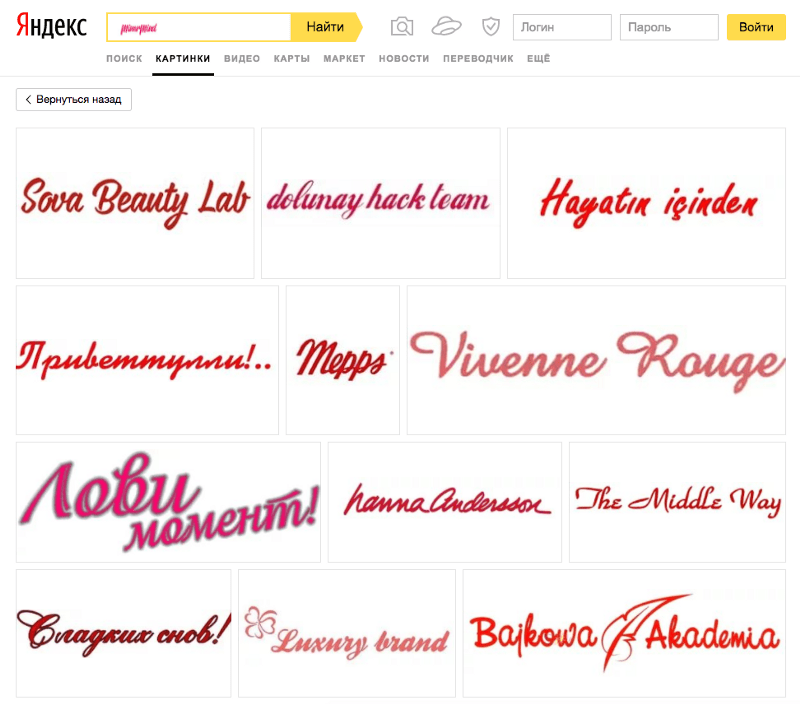
Как выбрать шрифт — руководство для начинающих — Офтоп на vc.ru
Дизайнер и разработчик Джонатан Уайт рассказал о базовых принципах работы с типографикой.
Один из самых важных навыков для дизайнера — это умение выбирать типографику, пишет Джонатан. Ведь текст — один из основных способов коммуникации дизайнера с пользователями. И типографика может как улучшить дизайн, так и сломать его.
Типографика одновременно сложна и прекрасна. Некоторые люди посвящают ей всю свою карьеру. К счастью, их работа хорошо задокументирована, так что у нас есть множество типографических онлайн-ресурсов.
Этот материал призван сформировать начальные навыки выбора типографики для своего дизайна, а также стимулировать на эксперименты со шрифтами и их комбинациями — в том числе и неизвестными.
Определите свою цель
Прежде всего нужно понять, в чем цель вашего дизайна. Какую информацию вы хотите донести? С помощью чего? В хорошем дизайне типографика соответствует цели.
Например, если вы создаете дизайн приветственной карточки, который в основном полагается на изображения, лучше выбрать шрифт, который подходит к стилю иллюстраций. Шрифт должен находиться в гармонии с остальным дизайном.
Выбирайте шрифт, соответствующий стилю иллюстраций
Если вы создаёте дизайн лендинга, в котором большую роль играют изображения, берите шрифт, который не будет отвлекать от иллюстраций. Шрифт в этом случае выступает как способ сделать акцент на значимой информации, несущей ключевой смысл.
Если изображения — главный элемент вашего дизайна, берите простые шрифты, чтобы подчеркнуть иллюстрацию
Определите свою аудиторию
Разобравшись с целью дизайна, определитесь с аудиторией. Этот шаг крайне важен, поскольку выбор шрифтов будет зависеть от возраста, интересов и культурного бэкграунда аудитории.
Например, некоторые шрифты лучше подходят для детей. Поскольку они только учатся читать, для них лучше всего подходят легкочитаемые шрифты с крупными и различимыми буквами. Хороший пример такого шрифта — Sassoon Primary. Его создала Розмари Сассун, основываясь на собственных исследованиях того, какие буквы легче всего считываются детьми.
Sassoon Primary
Другие шрифты лучше подходят для более взрослых детей. В таких шрифтах буквы подходящего размера, цвета — контрастные, а рукописного начертания и декоративных стилей нет.
Выбирая типографику, учитывайте аудиторию и её нужды. Проще говоря, ставьте себя на место пользователей.
Ищите вдохновение
Обратите внимание на работы других дизайнеров. Попытайтесь понять, как они определяли облик своей типографики.
Идеи для шрифтов
Если вы не знаете, какой шрифт выбрать, статья The 100 Best Free Fonts из CreativeBloq может быстро настроить вас на нужный лад.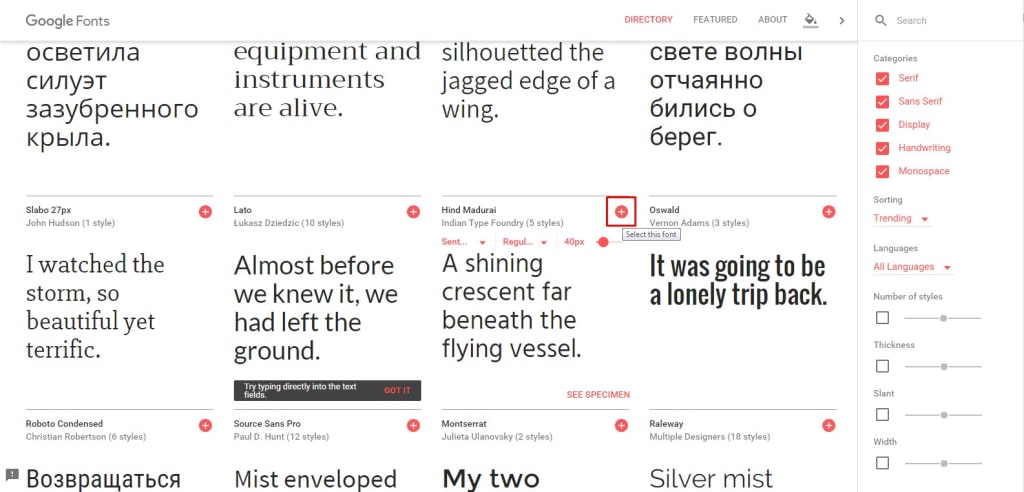
Другой полезный источник идей — это 100 Greatest Free Fonts Collection for 2015 от Awwwards. К тому же, Invision не так давно собрали огромный список ресурсов о типографике. Там источников идей предостаточно.
Чтобы посмотреть, как идеи выглядят на реальных сайтах, зайдите на Typ.io. Там собраны примеры шрифтов со всего интернета. К тому же внизу каждого образца шрифта есть его описание в CSS.
Помимо таких сервисов «для вдохновения», обратитесь к своим любимым сайтам и посмотрите, какие шрифты они используют. WhatTheFont — неплохой инструмент для этого. WhatTheFont — это расширение для Chrome, которое позволяет изучать шрифты в вебе, проводя по ним мышкой.
Идеи для сочетаний
Помимо просто шрифтов, ищите идеи для их сочетаний. Правильные сочетания не менее важны, чем сами шрифты. Благодаря правильно подобранному сочетанию шрифтов создаётся визуальная иерархия информации и улучшается читабельность дизайна.
В поисках вдохновения для сочетаний начните с Typewolf. Там собраны примеры сочетаний шрифтов с разных сайтов. Кроме того, на сайте есть рекомендации и статьи с глубоким разбором типографики. Настоящий кладезь информации.
FontPair — тоже хороший пример источника вдохновения для сочетаний шрифтов, особенно Google Fonts. Можно фильтровать комбинации стилей: например, Sans-Serif и Serif или Serif и Serif.
И, наконец, в сети есть множество коллекций хороших сочетаний шрифтов, собранных дизайнерами. Например, Typography: Google Fonts Combinations и Typography: Google Fonts Combinations Volume 2. Или просто введите в поиск «сочетания шрифтов» (font pairing) на сайтах вроде Behance и Dribbble.
Выберите свои шрифты
Вдохновившись и вооружившись исследованиями, вы, наконец, готовы выбрать типографику. Когда дело доходит до этого, держите в уме следующие принципы: интересный внешний вид, разборчивость и смысл.
Прежде чем выбрать шрифт, узнайте, для чего он создавался
Выбирайте шрифт, который подходит цели по общепринятым меркам и легко читается.
Избегайте слишком вычурных шрифтов в пользу простых и практичных. Также помните о том, зачем вам нужен шрифт. Например, некоторые шрифты лучше подходят для заголовков, другие — для основного текста.
Контент, который мигает или мерцает, может вызвать припадки у восприимчивых людей. Это может не только вызвать судороги, но, вероятно, будет раздражать или отвлекать пользователей в целом.
Избегайте мигания текста!Типографика — это большое дело. Неправильный выбор типографики может отвлечь пользователей от чтения. Очень важно сделать типографику читаемой , понятной и разборчивой.
Типографика существует, чтобы уважать контент
Типографика должна уважать контент таким образом, чтобы никогда не увеличивать когнитивную нагрузку пользователя.